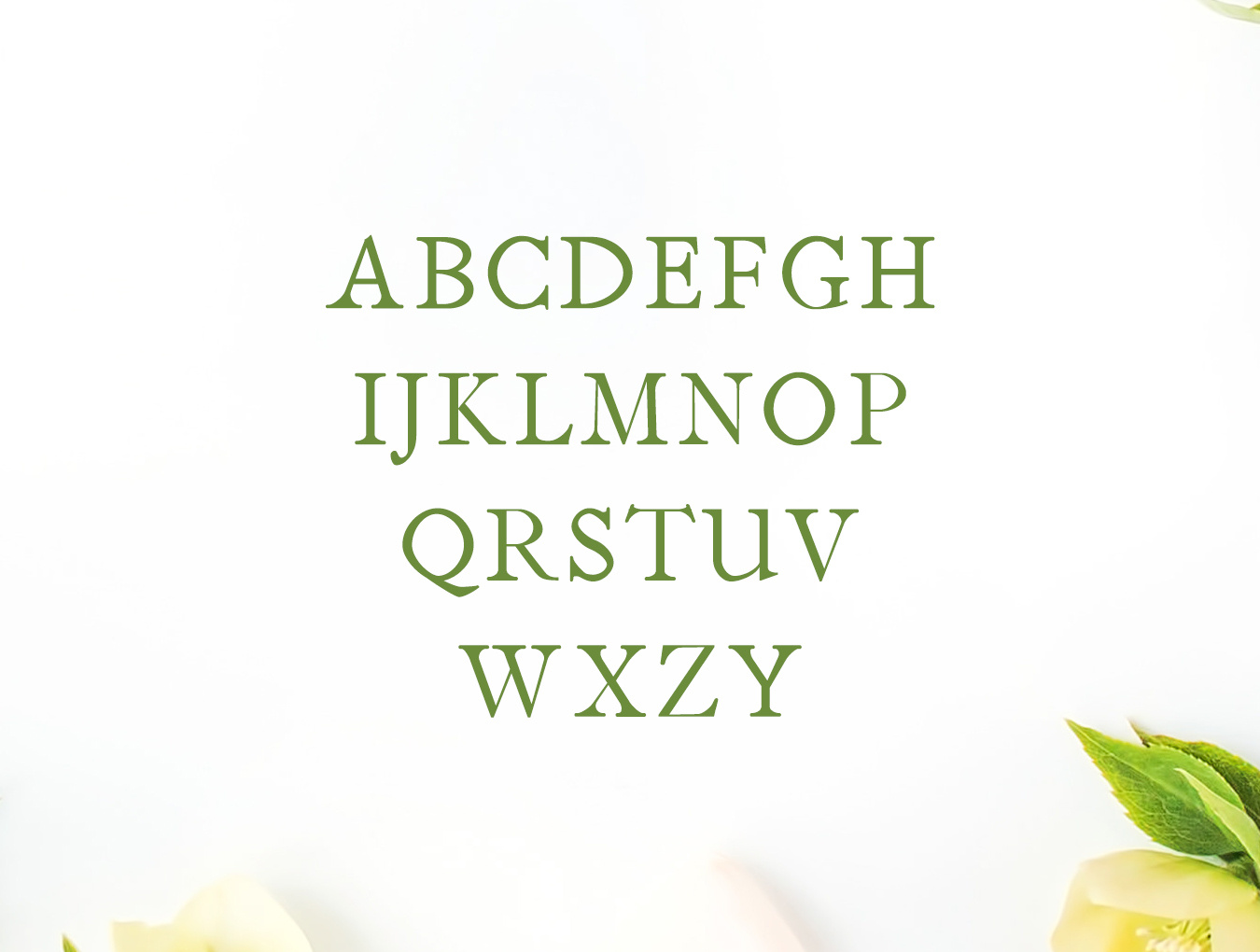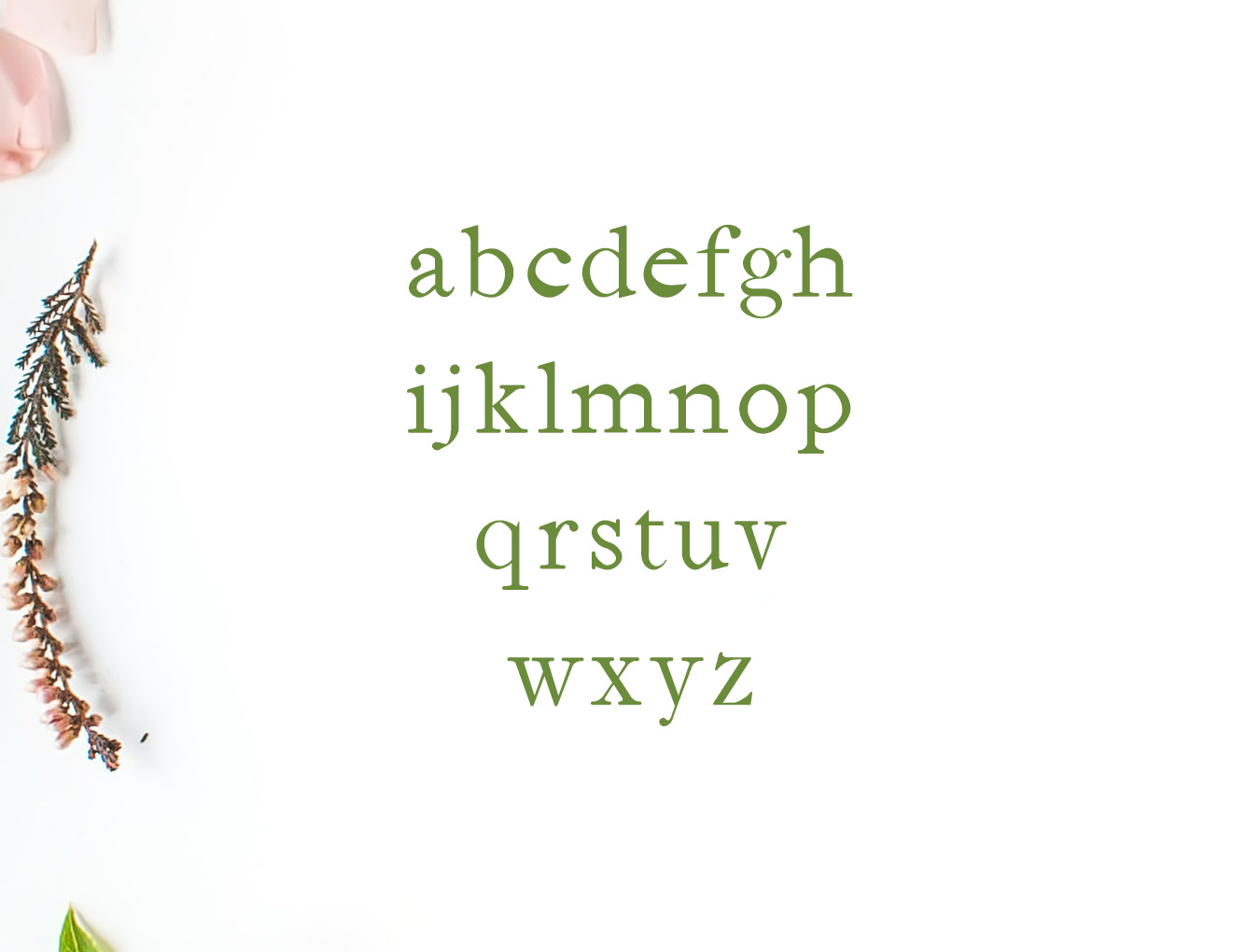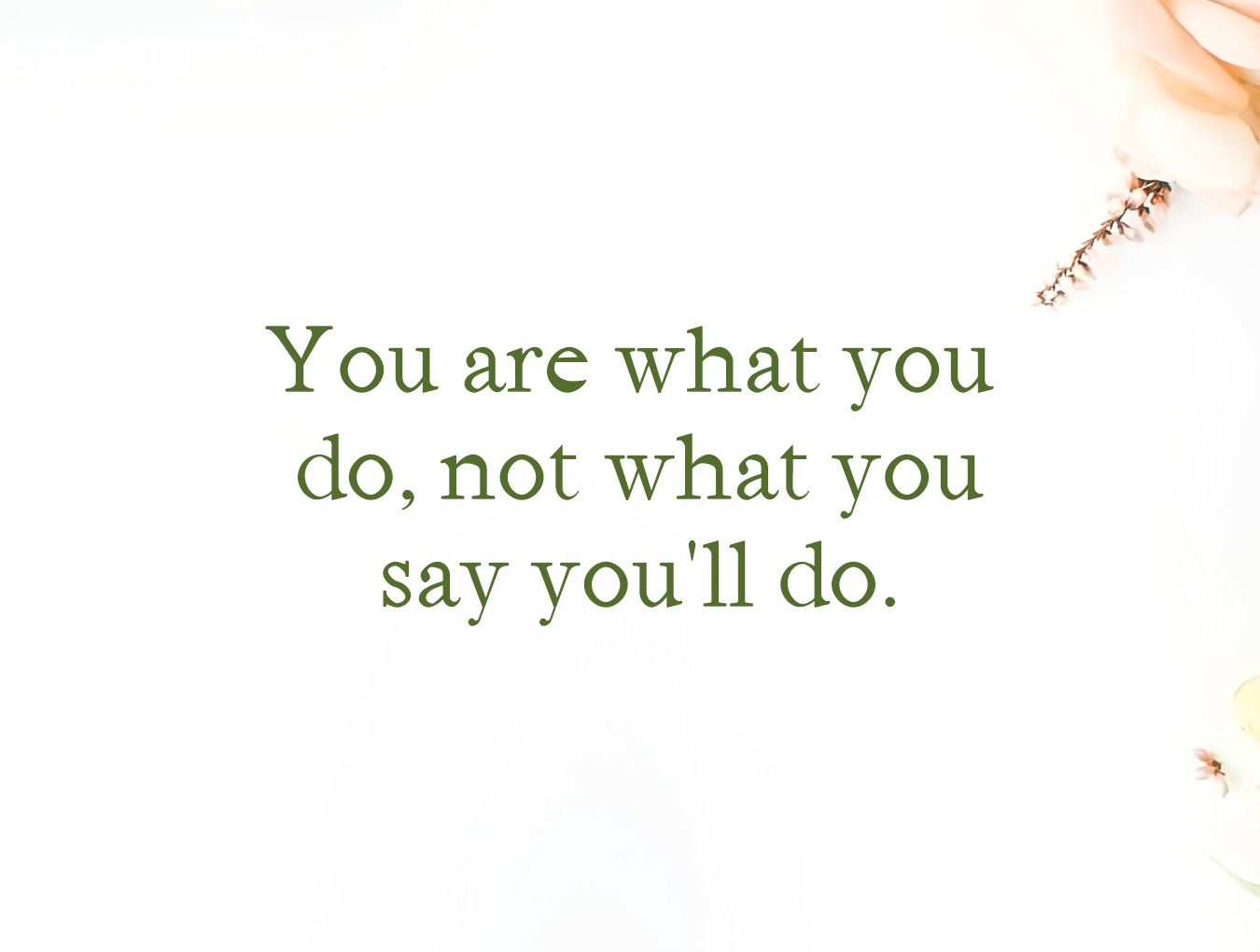
Jerricca Serif 4字体家庭装,Jerricca Serif字体
Jerricca Serif 4 Font Family Pack, Jerricca Serif Typeface
Jerricca Serif字体是一个简单的衬线字体系列,包含4个重量,它具有独特和现代的衬线外观和感觉。非常适合华丽的徽标,标题,网页布局和品牌。如果你想尝试一个优雅的外观,它看起来华丽,所有帽子都有宽大的间距,或者在大写字母和小写字母上完美无瑕。